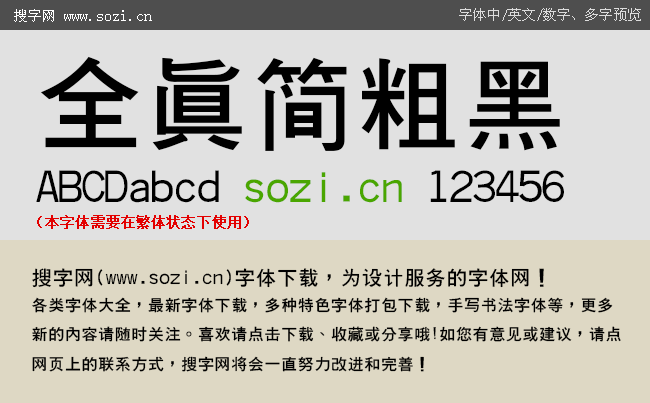
全真簡(jiǎn)粗黑
搜字網(wǎng)提供一款全真簡(jiǎn)粗黑下載,全真簡(jiǎn)粗黑是一款需要繁體輸入的粗黑字體,該字體緊湊,識(shí)別性強(qiáng),端正大方,整體風(fēng)格出色,適用于廣告設(shè)計(jì)、名片設(shè)計(jì)、包裝印刷、產(chǎn)品設(shè)計(jì)等應(yīng)用。